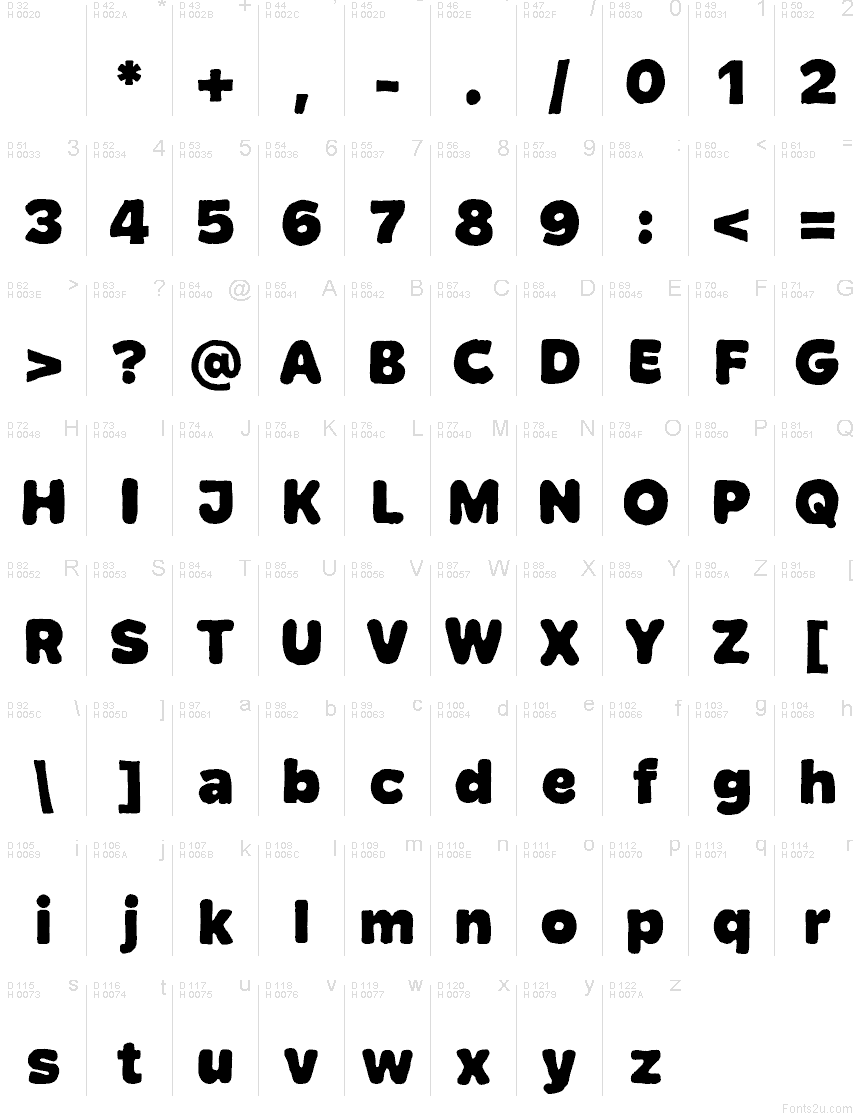
Blone Regular
Blone od Afkari Studio je bezplatné kreslené písmo s mäkkou, oblou siluetou a pohodovým nádychom komiksových príbehov. Písmená pôsobia skôr ako vymodelované než nakreslené, s výraznými zaoblenými tvarmi, tesnými krivkami a drobnými zárezmi v spojoch, ktoré udržujú živý rytmus namiesto prílišnej uhladenosti.
Hodí sa na obálky detských kníh, obaly sladkostí či hračiek, veselý branding kaviarní, návrhy nálepiek i krátke nadpisy na sociálne siete, kde potrebujete bezplatný font s priateľským a výrazným charakterom. Vďaka plným a jednoduchým tvarom funguje Blone skvele aj v titulkoch, skiciach log a veľkých nápisoch, ktoré majú pôsobiť hravo, bez toho, aby boli príliš sladké.